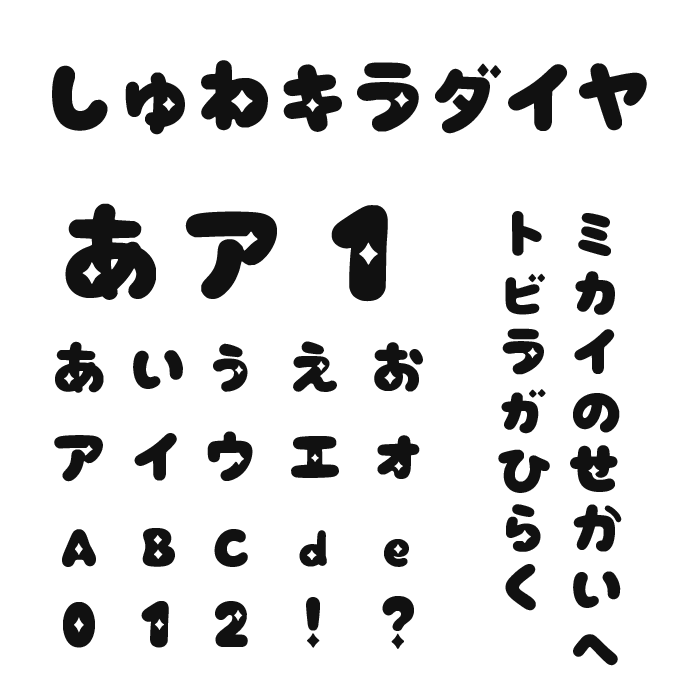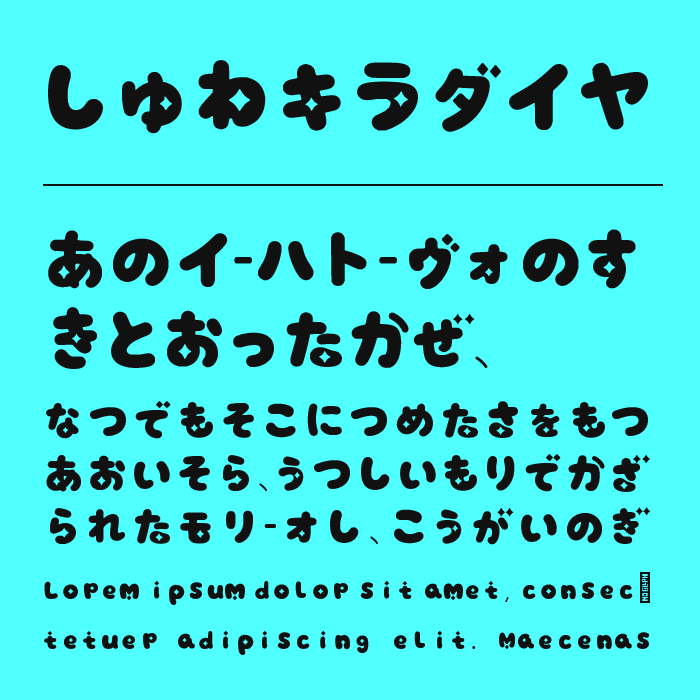
しゅわきらダイヤフォントは、太く丸みのある文字に、小さな突起や切り込みを加えたポップなデザインフォントです。
全体としてはぷっくりと柔らかい形ですが、文字の端や内側にひし形のようなアクセントが入り、ただの丸文字とは少し違ったキラキラ感があります。
アイドルや推し活、ファンシー系のデザイン、子ども向けコンテンツ、SNSのサムネイルなど、明るくにぎやかな場面と相性が良さそうです。太さがあるのでタイトルや見出しにも使いやすく、小さくしても丸いシルエットがしっかり残ります。かわいさの中に少しだけ遊びを足したいときに使いやすいフォントです。